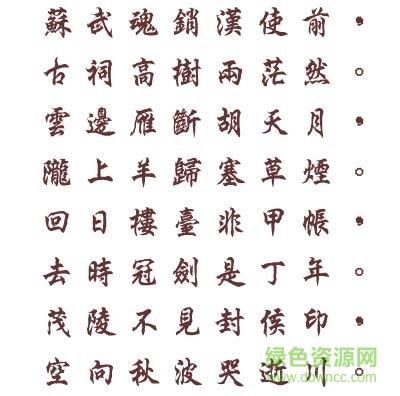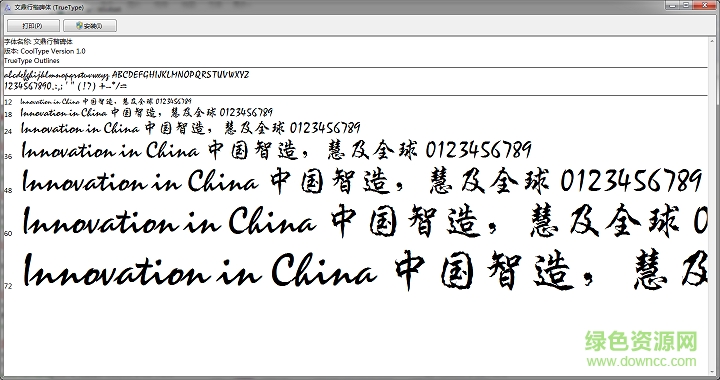
文鼎行楷碑體是一款像帶有波浪的中文簡體字體。該字體的周邊坑坑洼洼,像波浪的效果,還是很有特色,藝術制作中比較常用。趕快下載體驗吧!
學習行楷字諸多因素交互影響,既有筆順錯別字問題,又有橫平豎直極端僵化寫法;既要因材施教,又要普及提高;既可借鑒楷書基礎(快速過渡),又可直接進入行楷學習(立足本體);還有書寫者學習態(tài)度等等,都需要適時綜合考慮,從而達到書寫規(guī)范美觀、便利流暢的教學效果,關鍵在于平時落實科學的教學計劃(進度、教法等)、合理的書寫學習和有效的訓練。事實上也如此,正因其隨意和靈動的特點,行楷字體的學習難度,不亞于楷書等字體。由楷而行,應有其內在的規(guī)律可循,不能簡單的理解為是楷書筆畫的疾書。必須循序漸進,逐步提速。
還應看到,過分強調楷化,容易造成書寫僵化呆板,缺少實用意識,影響書寫結構的靈活以及速寫的節(jié)律等。而過度強調行意忽略楷書基礎,又容易造成字形結構的零亂松散,甚至草化,產生閱讀困難識認分歧。只有楷行兼顧,直曲方圓收放有度,勻稱呼應,連帶適當,穩(wěn)扎穩(wěn)進,才可能學好行楷手寫體。